设计师在进行设计时,字体是否运用得合适,能直接决定版面的成败。选择合适的字体能准确地传达信息和美感,但是对于很多设计新手们来说,选择字体实在有点难度。在各种搜字体网上搜来搜去也找不到满意的,好不容易找到了满意的又是要付费的,不清不楚的用了会有很多不必要的麻烦。小编今天要为新手设计师推荐几款字体视界上免费商用的字体,帮助大家解决这个令人头秃的问题。
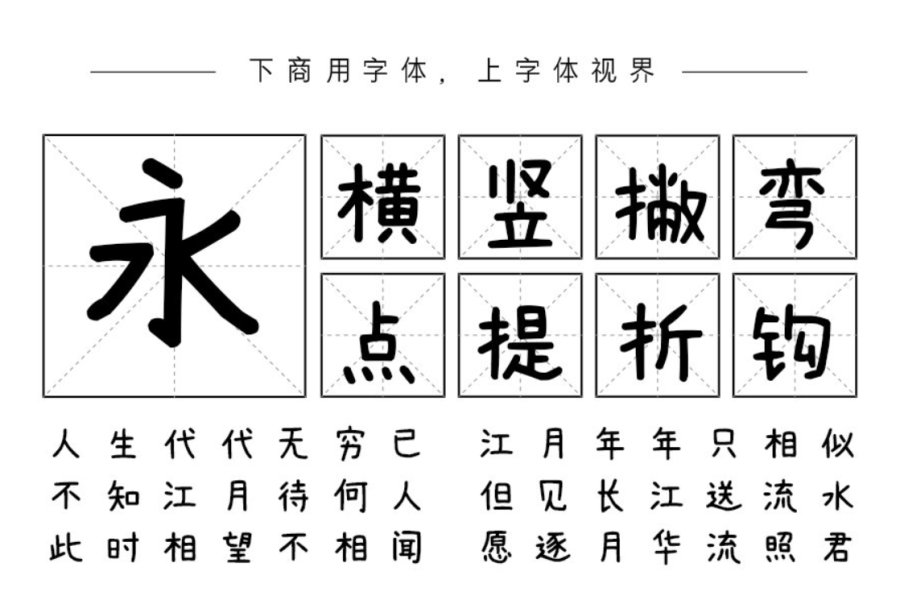
来自素材集市的首款原创字体下载,“素材集市康康体”是一款萌系可爱手写风格中文字体,字库共 2623 个汉字和字符。喜欢的卡通手写趣味字体的设计师们可以下载使用。
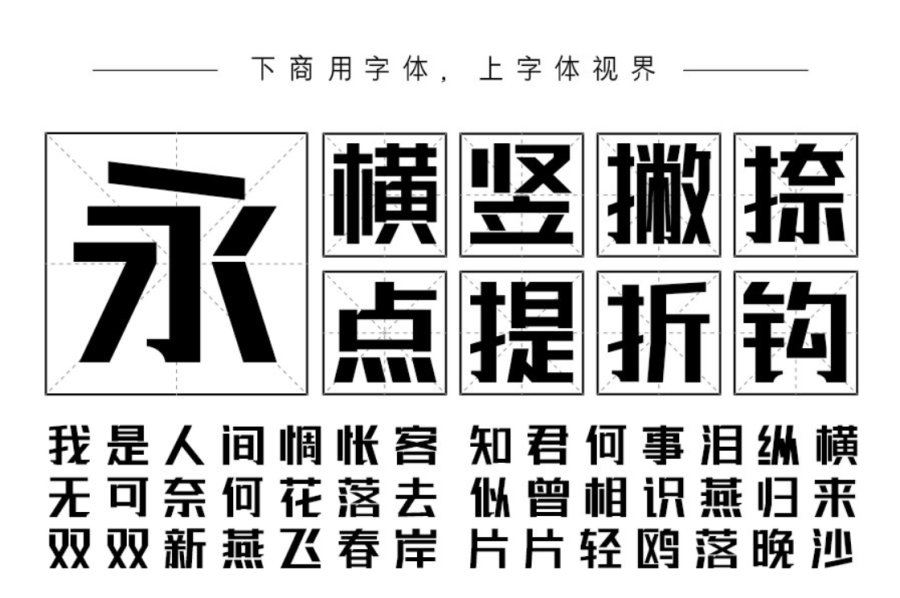
“联盟起艺卢帅正锐黑体”是一款非常刚性的免费可商用标题字体。这款字体整体方正,笔触粗实,字形厚重有力,但又不乏设计感,整体感觉非常不错。适用于大标题、包装设计、海报设计等应用。
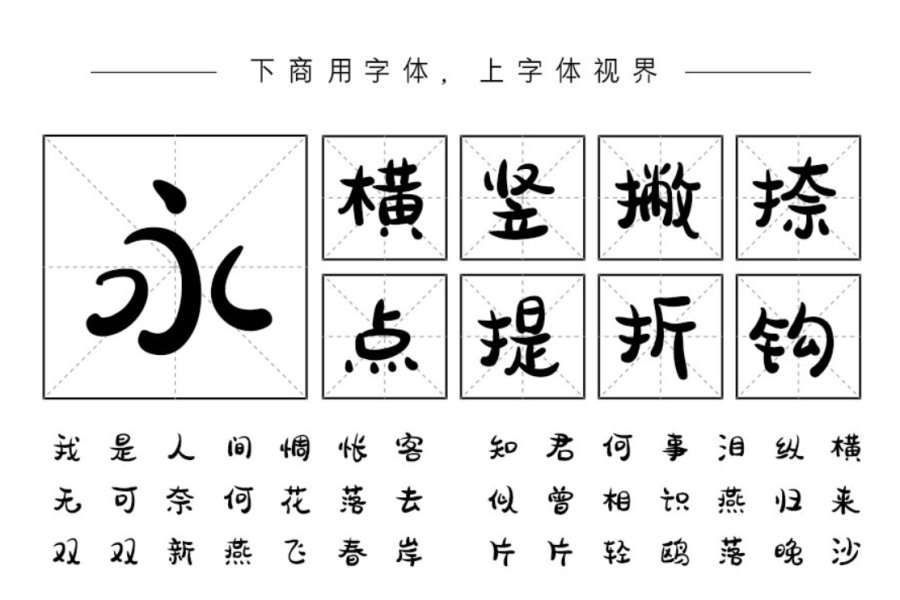
“胡晓波骚包体”是由设计者胡晓波推出的三款免费商用字体之一,字体采用了萌趣可爱的卡通字体设计,整体字形圆润饱满。适用于大标题、包装设计、海报设计等应用。
有时因为字库字体太多不知选择哪种,或者自我感觉字体越酷才是越好看,从而导致画面感档次不高。选择字体前需要了解各字体的气质特征,才能对症下药。小编为大家推荐的三款字体应用广泛,您可以保存图片点击寻找图片上的字体了解更多字体信息。